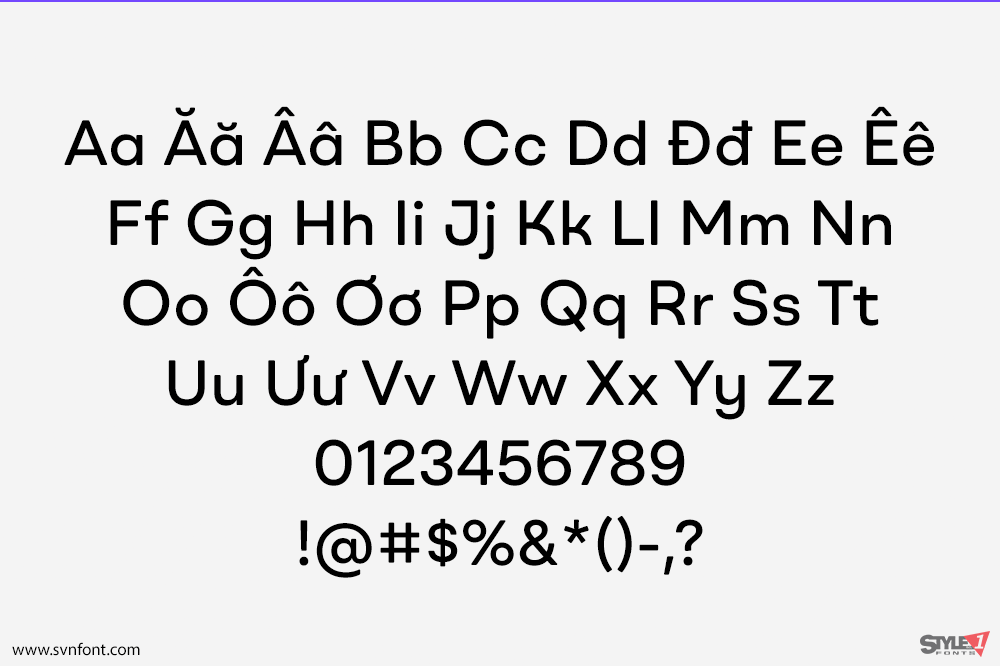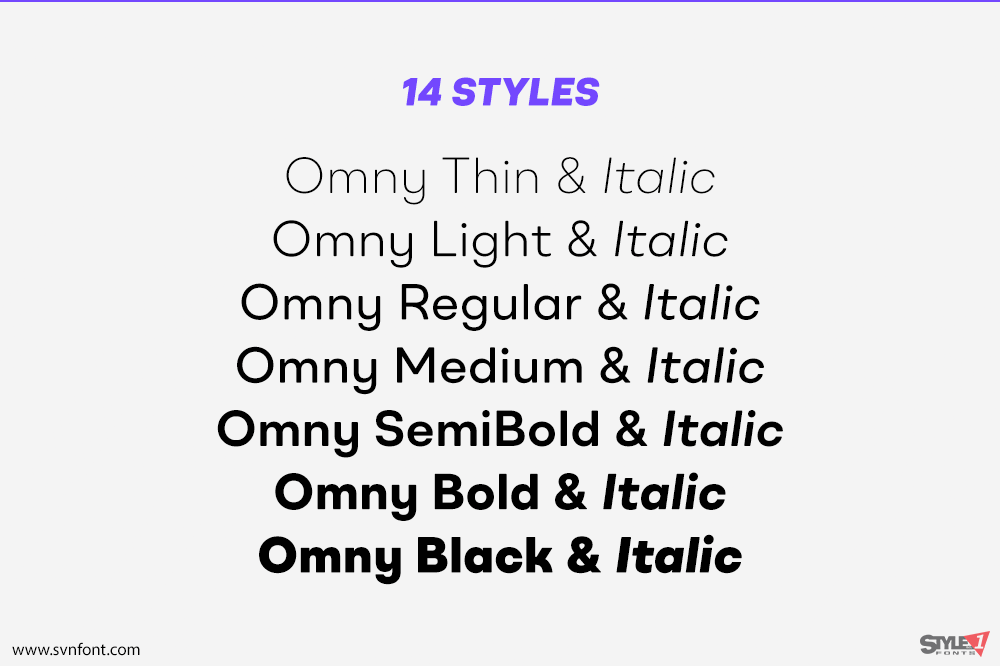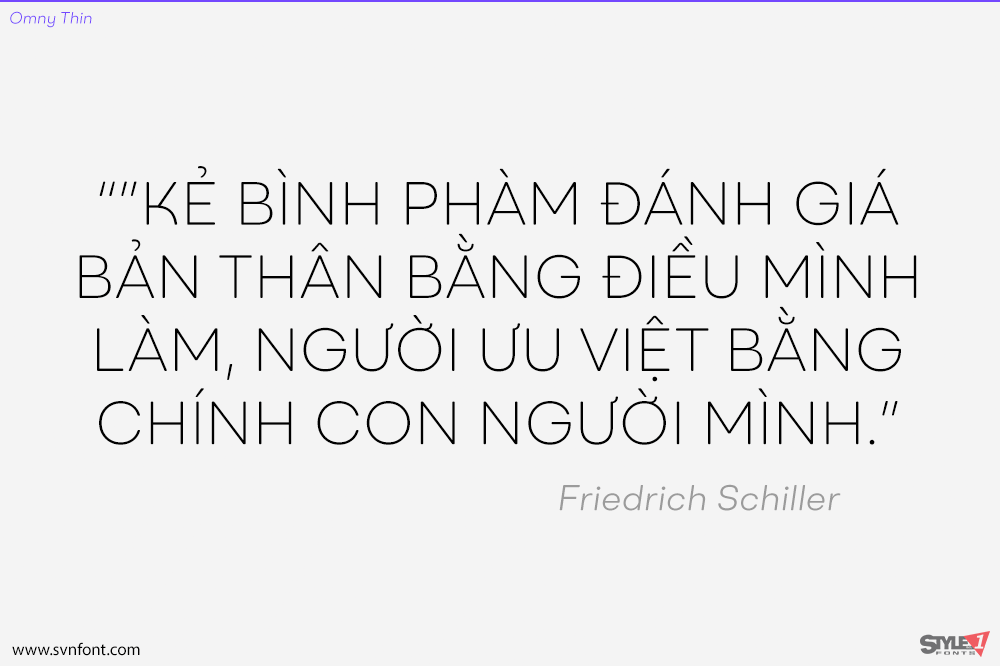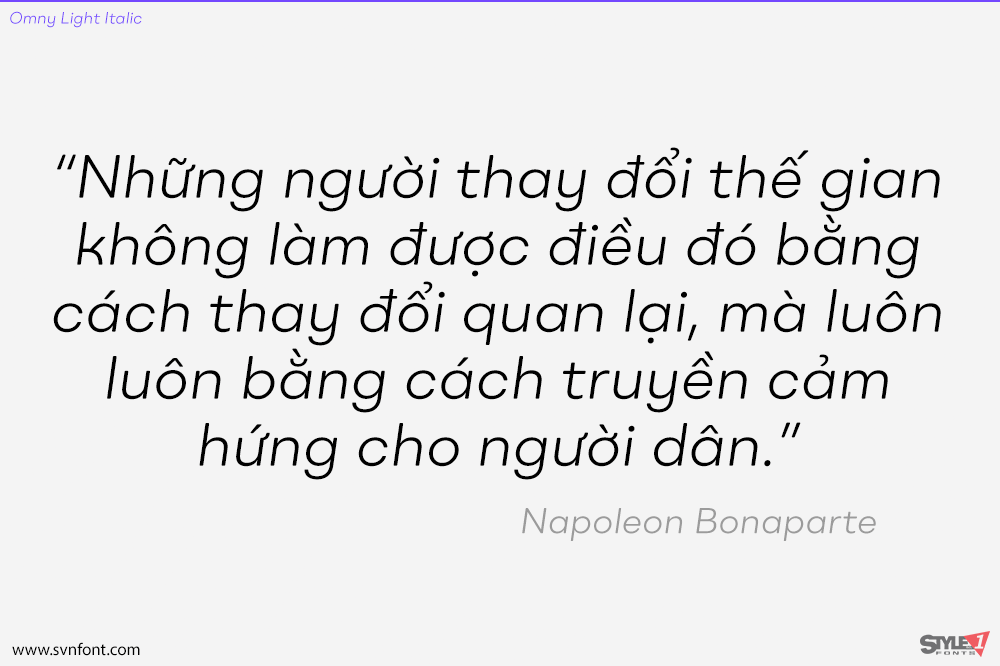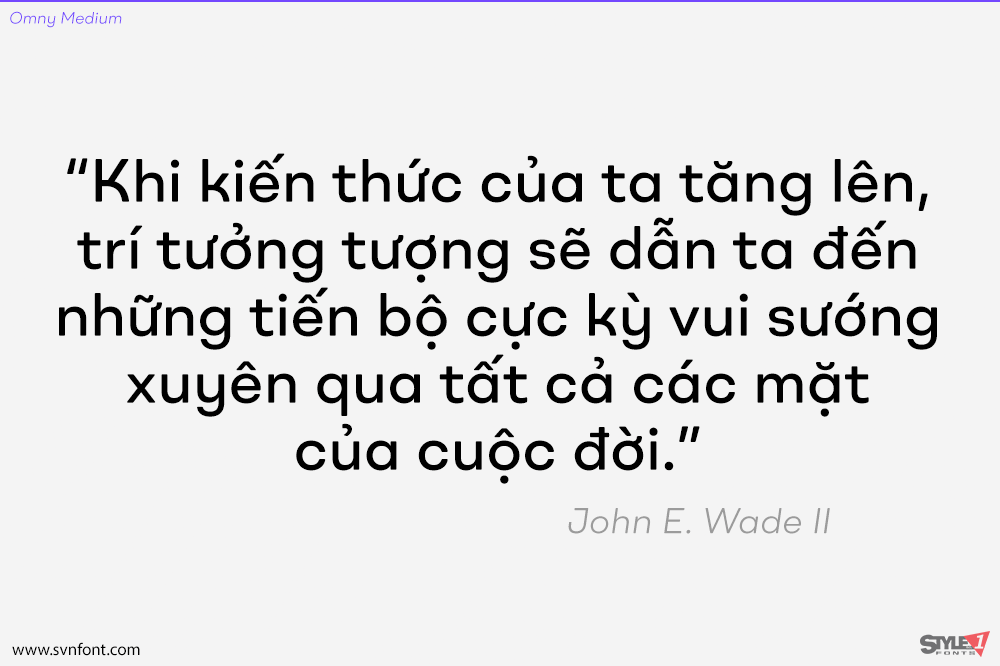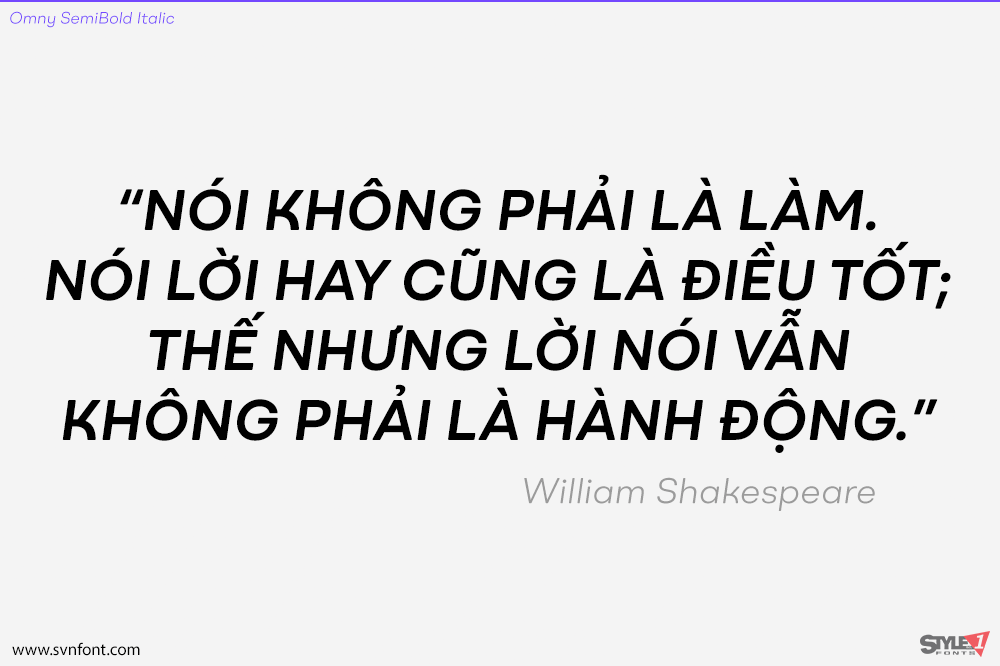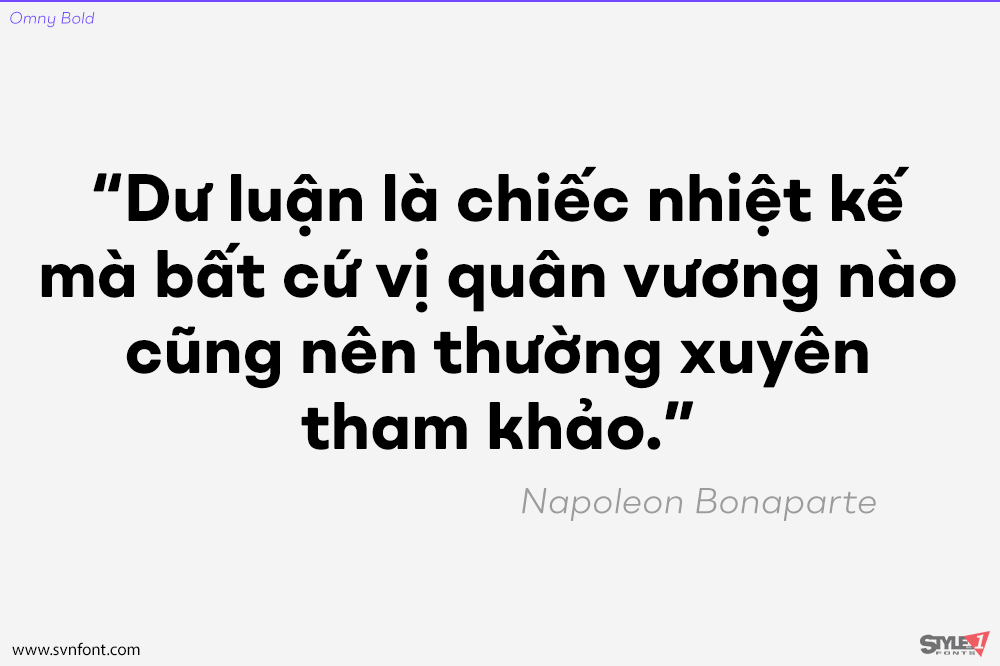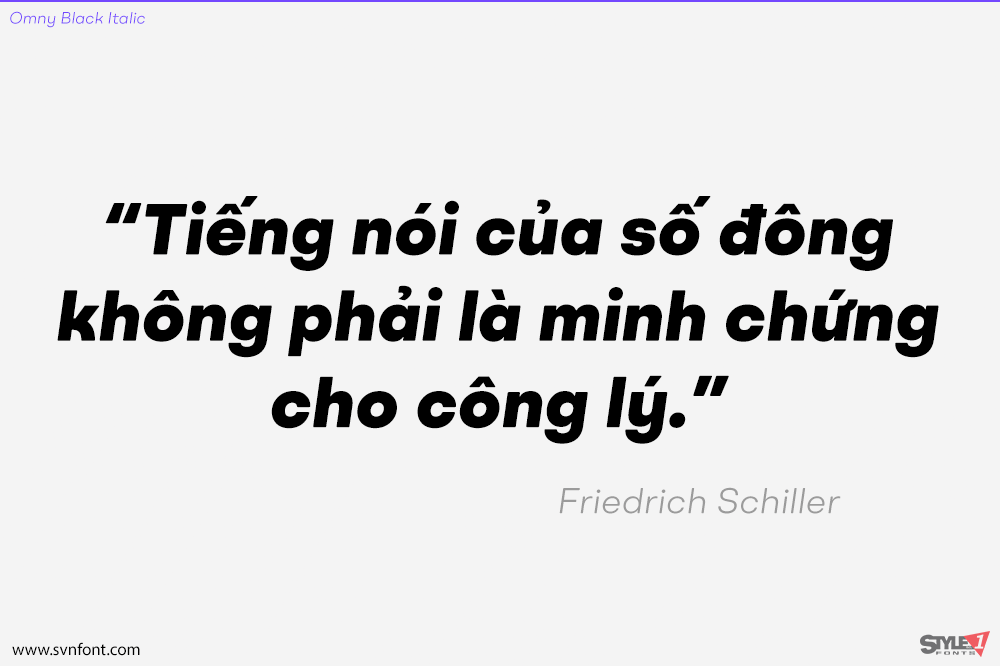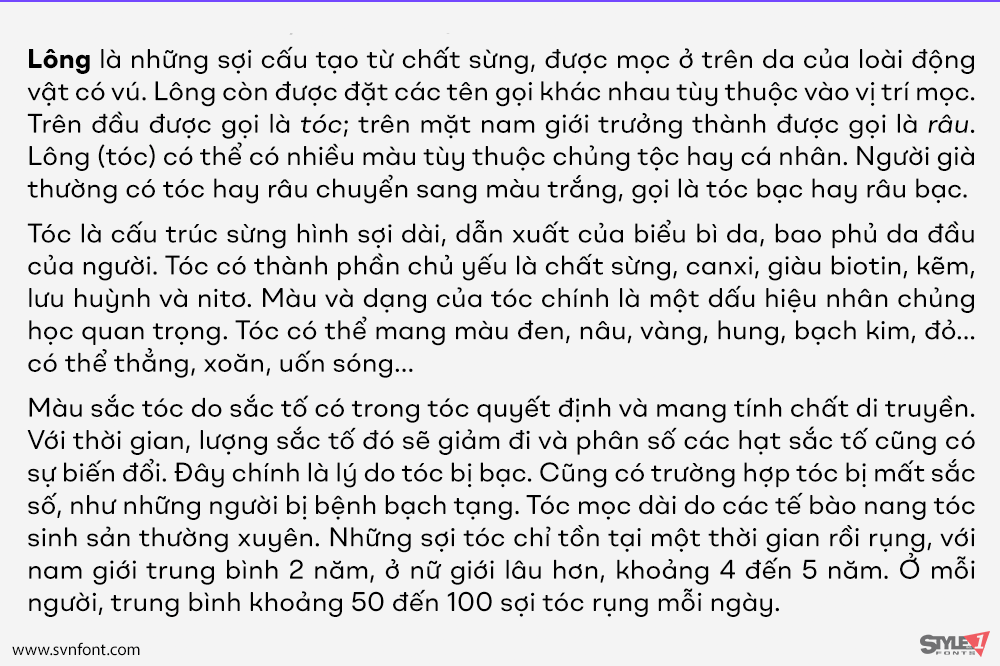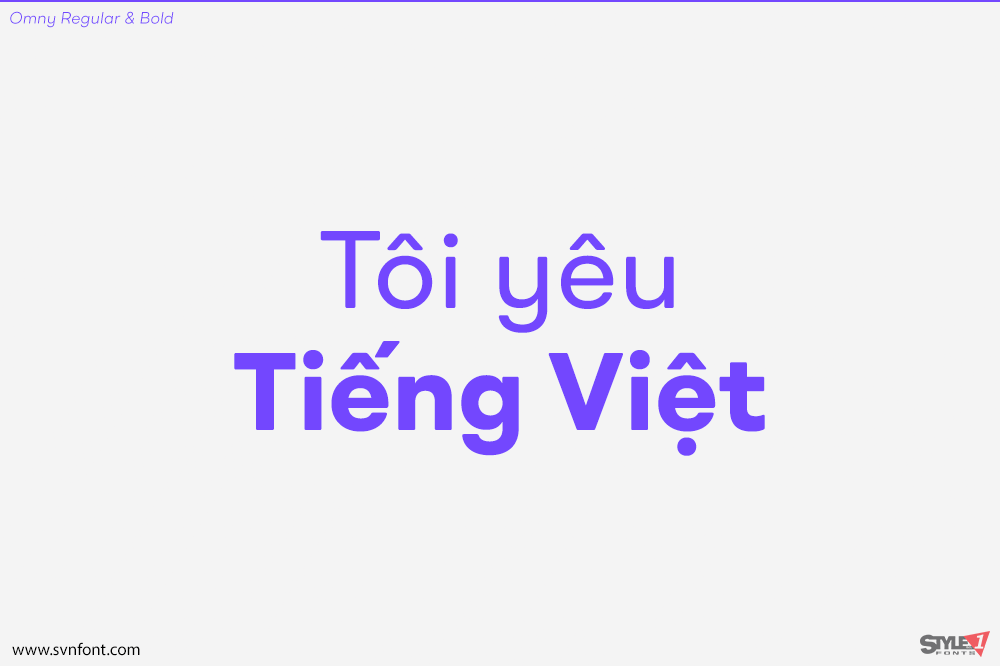
BR Omny là một phông chữ sans serif hình học bo tròn, dựa trên một khung hình học mềm mại với cá tính tự tin và thân thiện. Bộ phông này gồm 7 độ đậm, từ Thin đến Black, cùng với các kiểu chữ nghiêng tương ứng. Nó hỗ trợ bộ ký tự ‘Extended Latin’, cung cấp khả năng hỗ trợ cho hơn 200 ngôn ngữ dựa trên tiếng Latinh. BR Omny cung cấp hỗ trợ in ấn nâng cao với các tính năng OpenType như ký tự thay thế (alternates), dạng chữ hoa/thường (case forms), phân số và số không gạch chéo (slashed zeros). Nó đi kèm với nhiều bộ số khác nhau và lý tưởng cho in ấn, web, xây dựng thương hiệu, quảng cáo, xuất bản, trò chơi và ứng dụng di động.
Nhà thiết kế: Christoph York
Nhà phát hành: Brink